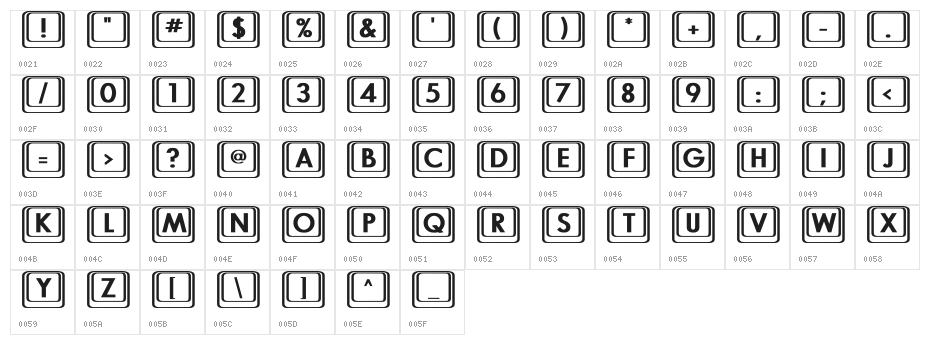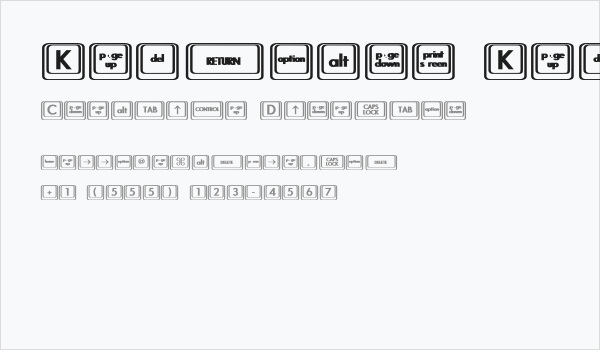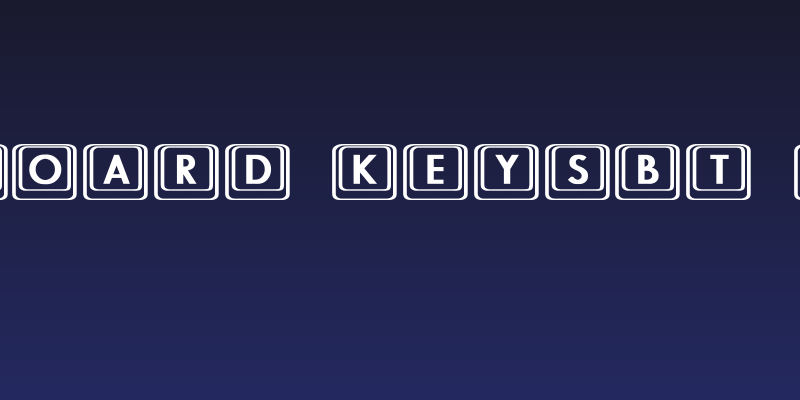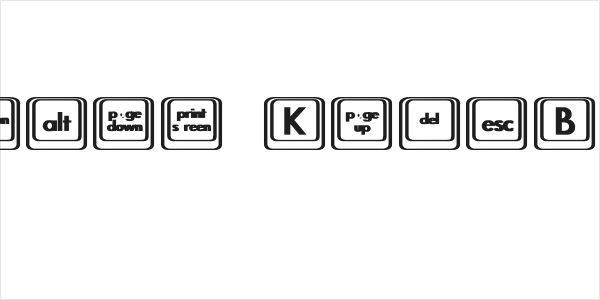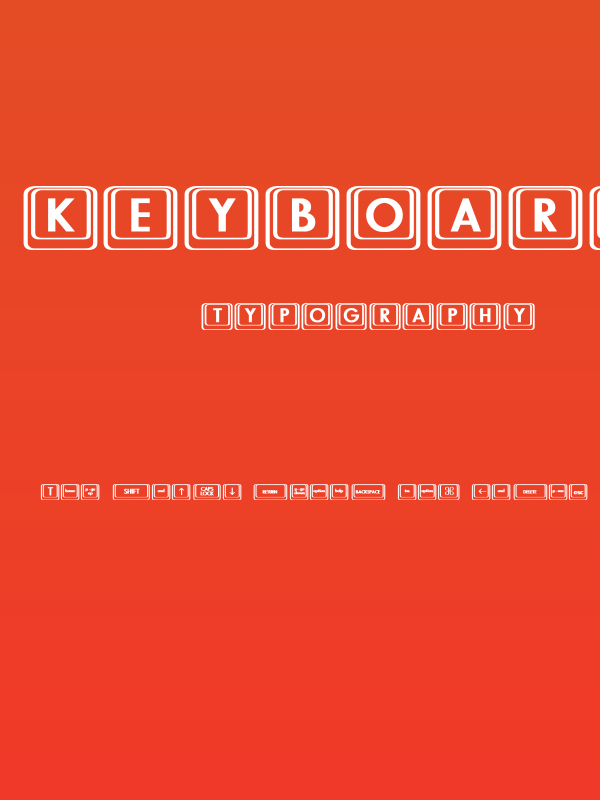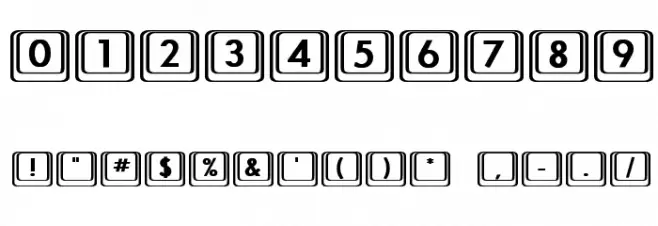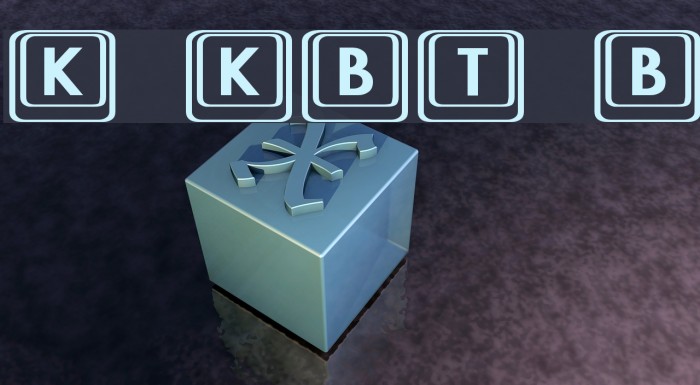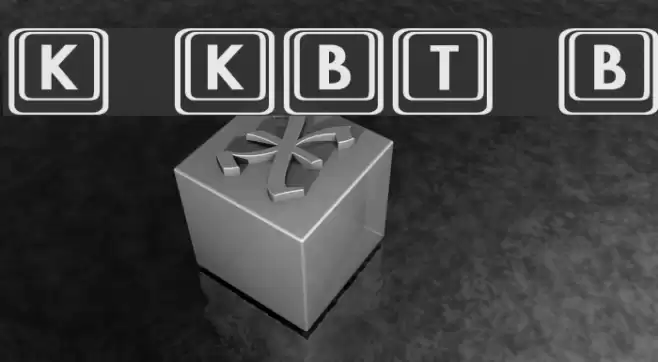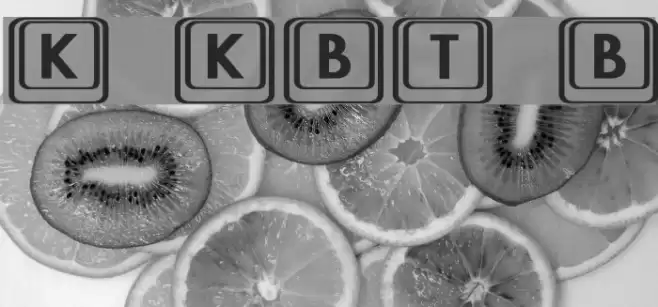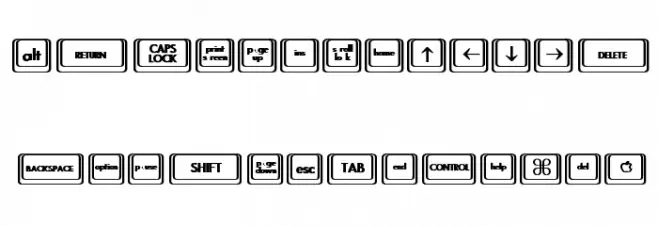
Keyboard KeysBT Bold Font
| Caz de utilizare | Logos, Headlines, Digital Interfaces |
| Proiecte propuse | Ideal for tech-related designs, digital interfaces, educational materials, or any project needing a modern, digital look. |